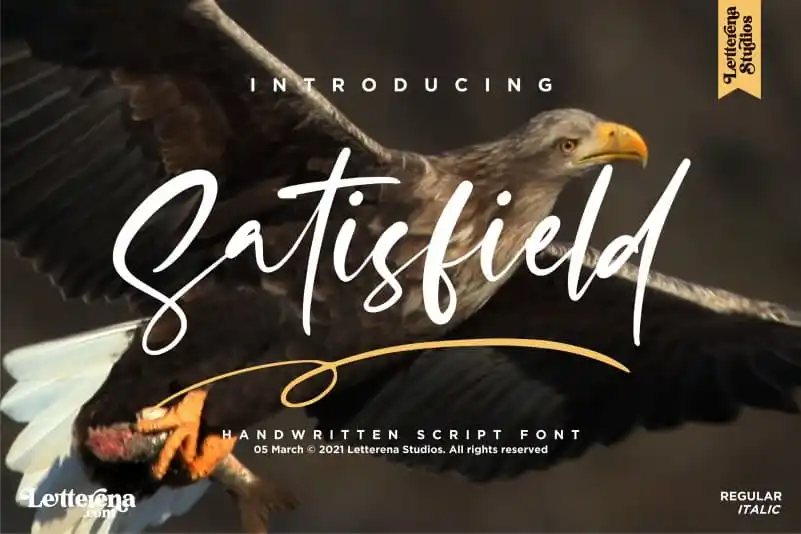
Satisfield Script Font – Download Grátis
A Satisfield Script Font é uma delicada escolha para projetos que exijam um toque elegante e sofisticado. Desenvolvida pela Letterena Studios, esta fonte escrita a mão oferece uma variedade de opções perfeitas para diversos tipos de projeto. Ela se destaca como uma opção ideal tanto para logos e campanhas de branding quanto para design de móveis de consumo, embalagens de produtos, mugs, cartões postais com citações, anúncios, sacolas de compras, t-shirts, capas de livros, cartões de nome, convites, cartazes especiais e até mesmo para marcas únicas. Com uma textura única que transmite conforto e elegância sem comprometer a eficácia do design, a Satisfield Script Font é perfeita para qualquer projeto em que você deseja adicionar um toque de sofisticação e personalidade.